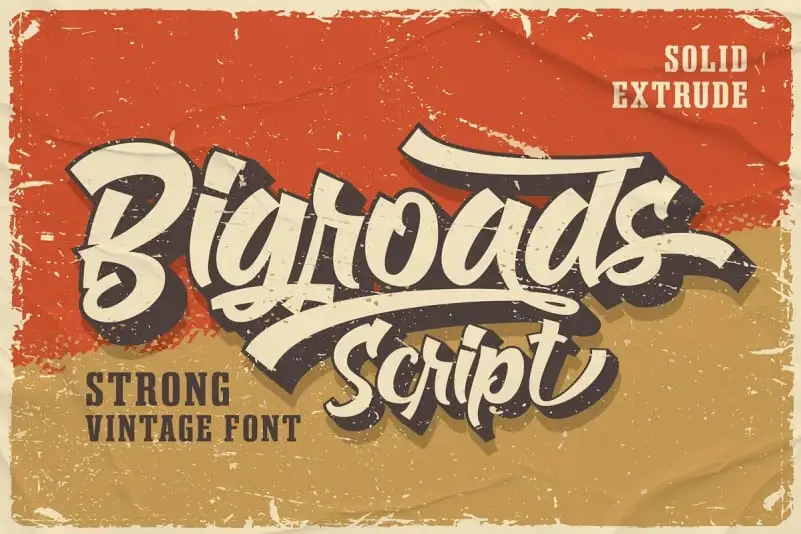
Bigroads Bold Script Font – Download Grátis
Na categoria das fuentes script, a Bigroads Bold é uma escolha irresistível para quem busca um tom nostálgico, desenhado especificamente para o look retro dos anos 80 e 90. Inspirada por estilos vintage, esta fonte foi criada em conjunto com técnicas de escrita manuscrita, resultando em movimentos dramáticos que dão vida à letra. Perfeita tanto para projetos modernos quanto para aqueles que desejam uma pitada retro, a Bigroads Bold Script se destaca como uma ótima opção para qualquer projeto criativo em busca de um toque único e imediatamente reconhecível. Seja você um designer gráfico ou um amante dos bons recursos digitais, é provável que encontre nesta fonte a solução perfeita para dar vida a seus próximos projetos, proporcionando uma atmosfera inebriante e natural de nostalgia.